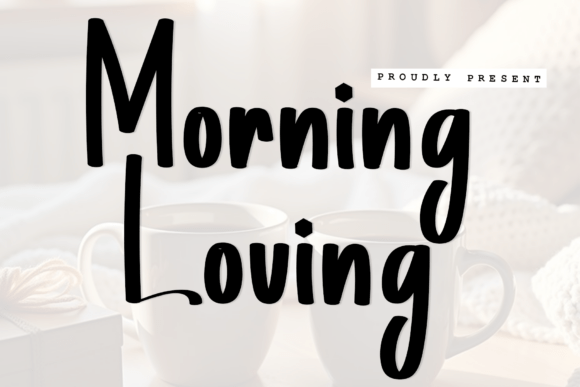
Morning Loving
إذا كنت تبحث عن أصول عالية الجودة مثل Morning Loving، فإن هذه الحزمة المميزة هي خيار رائع لمشاريعك الإبداعية.
سواء كنت تقوم بإنشاء منتجات الطباعة عند الطلب أو دعوات الزفاف أو رسومات وسائل التواصل الاجتماعي، فإن Morning Loving هو الخيار المثالي.